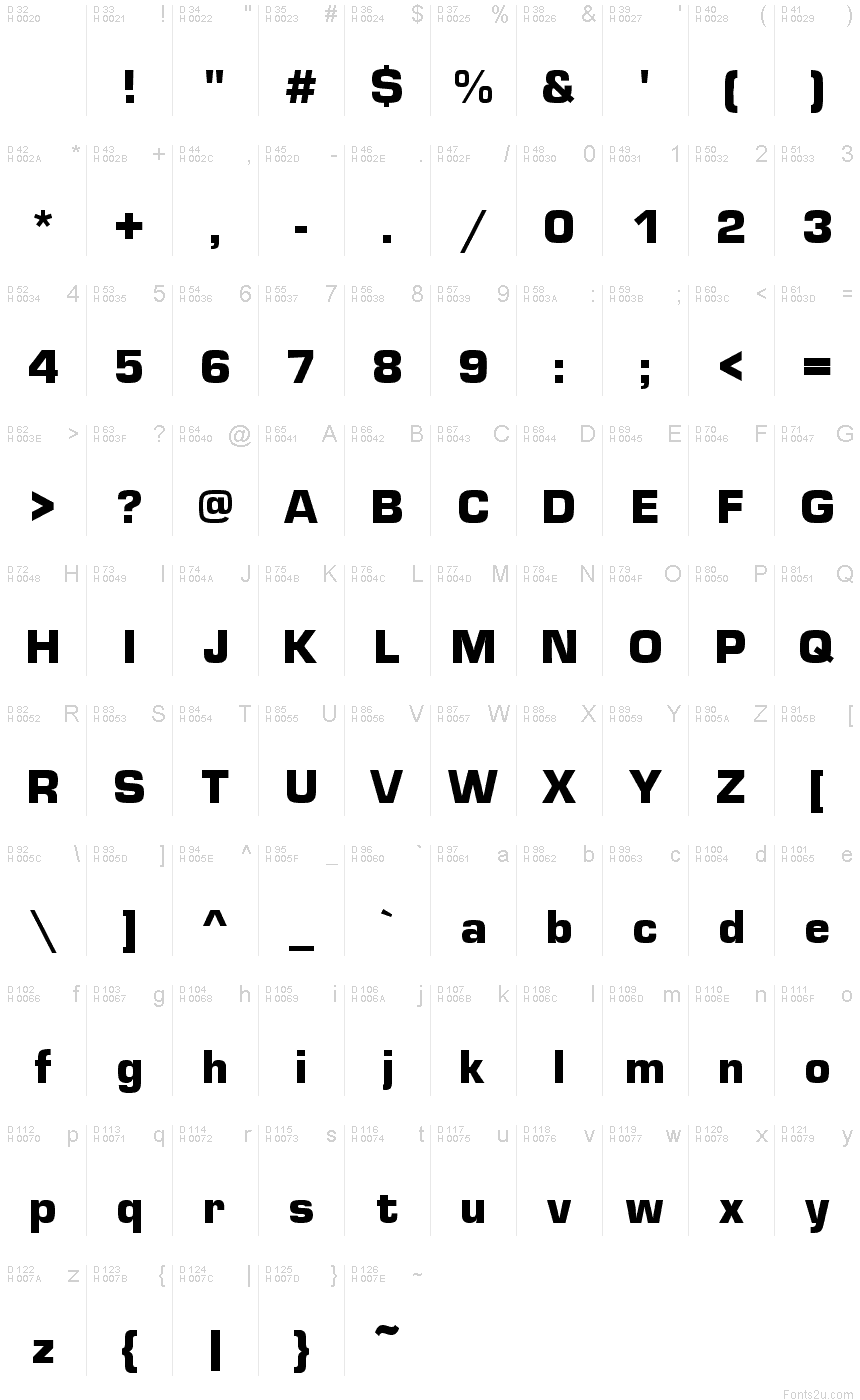
由 Mgi Software 推出的 Eurostar Black 是一款免费的超粗无衬线字体。其宽阔的字面、厚重的笔画以及微圆的边角,赋予了字体紧凑而浓郁的视觉感,第一眼便极具冲击力,同时兼顾了良好的易读性。Eurostar 系列具有工业化且近乎模块化的韵律,使得该字重在需要紧凑的字标或强力标题的项目中表现尤为突出。
使用 Eurostar Black,科技品牌、电竞战队、包装设计、海报、标识以及应用启动页的标题和 Logo 都能获得一种厚重、自信的质感,即便在远处也清晰可见。这款免费字体在短句和醒目的标题设计中尤为出色;建议保持文案简洁,并放大字号以达到最佳视觉效果。正文建议搭配轻盈的几何无衬线体,以平衡其强健有力的字形。